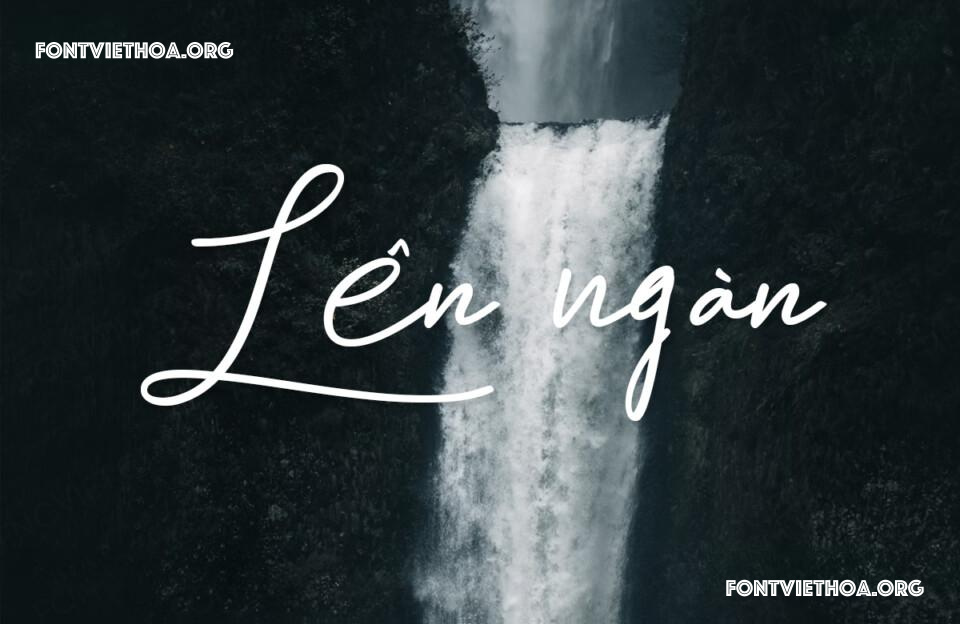
Tên font: Font Việt hóa VIP Capricious Ambrosia
Tác giả: Letterhanna Type Foundry
Font Việt hóa VIP Capricious Ambrosia là một trong những font chữ viết tay thú vị và được ưa chuộng hiện nay. Với thiết kế độc đáo và tinh tế, font này phù hợp cho các thiết kế thiệp mời, thiệp cưới, và nhiều ứng dụng khác.
Font này có thể được sử dụng trong nhiều lĩnh vực khác nhau, từ thiết kế đồ họa, thiết kế web, đến in ấn và xuất bản.